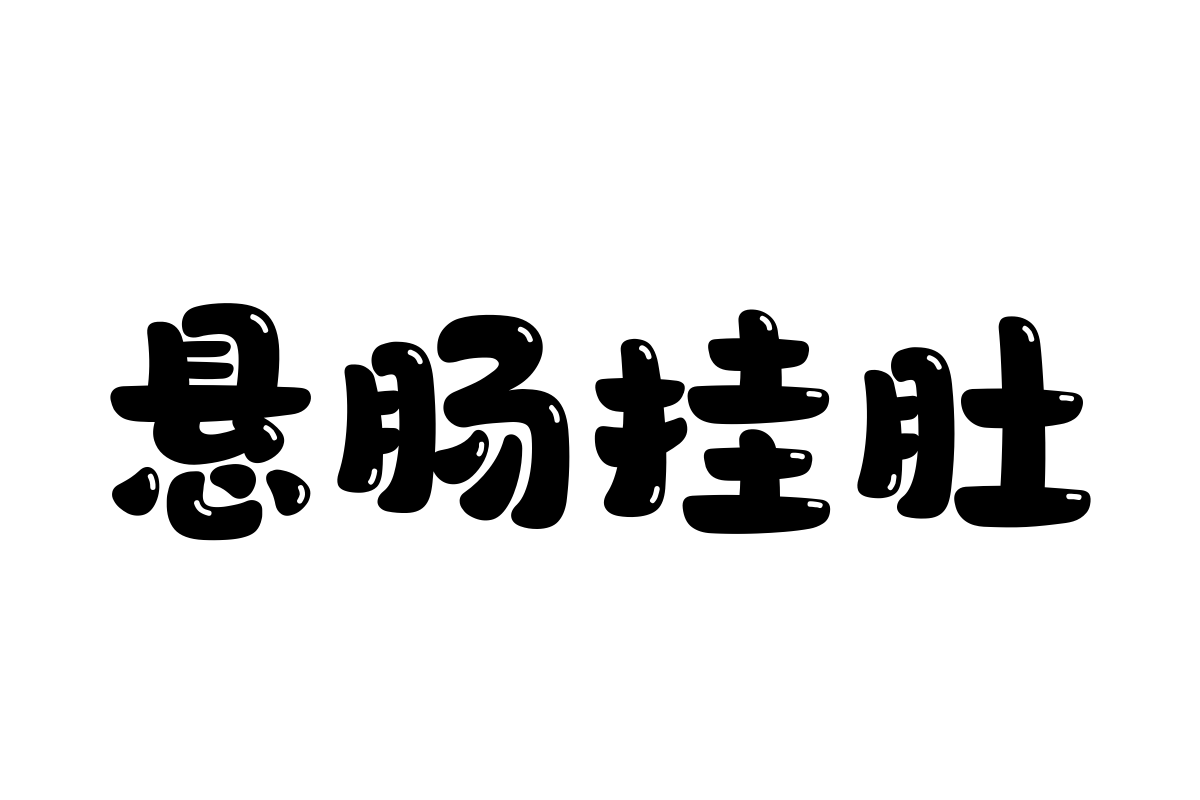
汉仪铸字果汁软糖是一款独特的字体,它结合了传统书法与现代设计元素,创造出一种既具有艺术感又不失实用性的字体。这款字体的特点在于其独特的笔画结构和流畅的线条,使得每一个字都显得生动有趣,仿佛可以品尝到果汁的甜美。
该字体适用于各种需要展示文字美感的场合,无论是海报、广告、书籍还是网页设计,都能展现出其独特的魅力。同时,由于其独特的风格,也使得这款字体成为了一种时尚的象征,受到许多人的喜爱和追捧。